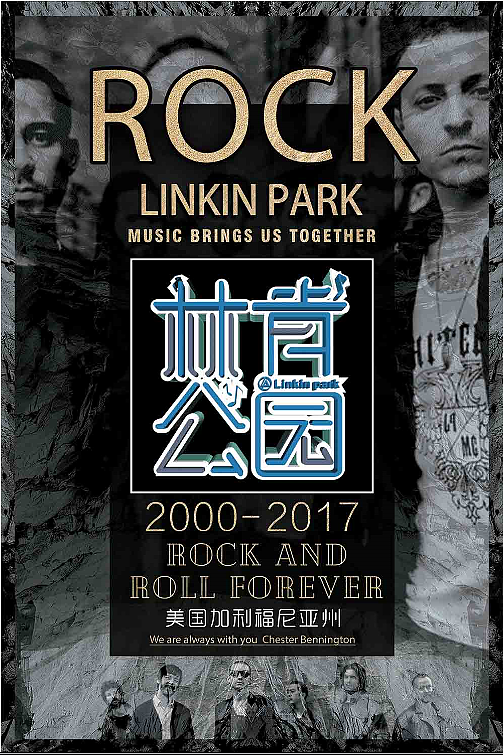
林肯公园(Linkin Park)
这次主要对字体做了立体层次感设计,从L型开始延伸并得到线稿;最后做了2组不同海报效果。 Linkin Park的歌曲陪伴了许多人的童年,主唱查斯特虽然离开了,但你一直活在我们心里,愿天堂没有痛苦,这一次的字体海报设计纪念我们心中永远的Linkin Park!爱你10年了。感谢你陪伴了我们的青春
字体全部采用钢笔工具完成-使用软件:CDR+PS
字体立体效果
字体字形线稿